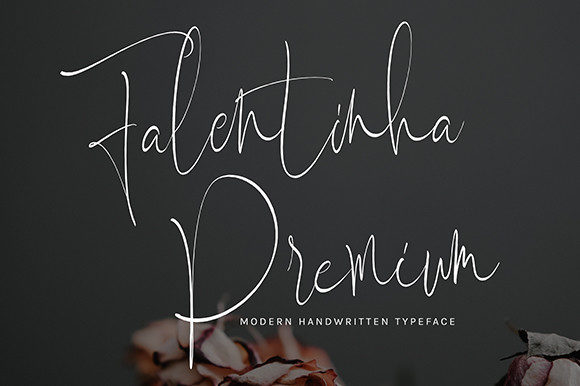
Falentinha Premium
การค้นหาองค์ประกอบการออกแบบที่เหมาะสมอาจเป็นเรื่องท้าทาย แต่ Falentinha Premium นำเสนอคอลเลกชันที่โดดเด่นซึ่งช่วยยกระดับงานของคุณได้ทันที
สร้างขึ้นอย่างแม่นยำ Falentinha Premium ให้เวกเตอร์ที่สะอาด พิมพ์ตัวอักษรที่ราบรื่น และใบอนุญาตเชิงพาณิชย์เพื่อความสบายใจ
ไม่ว่าคุณจะสร้างผลิตภัณฑ์ POD (Print on Demand) คำเชิญงานแต่งงาน หรือกราฟิกโซเชียลมีเดีย Falentinha Premium ก็เหมาะสมอย่างยิ่ง